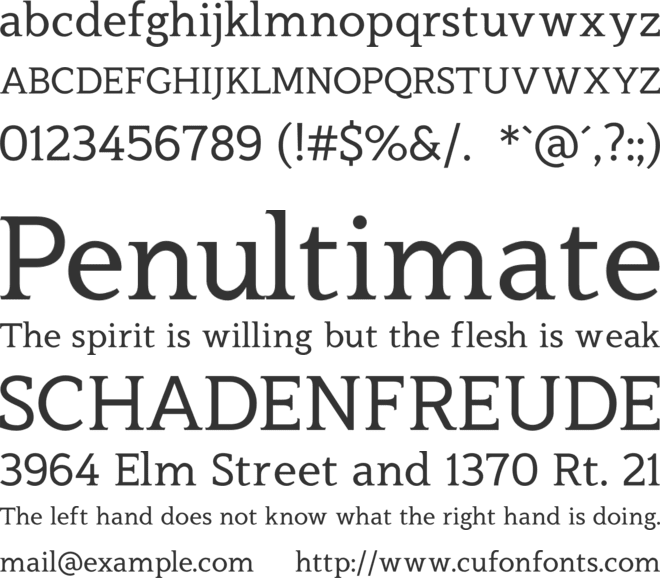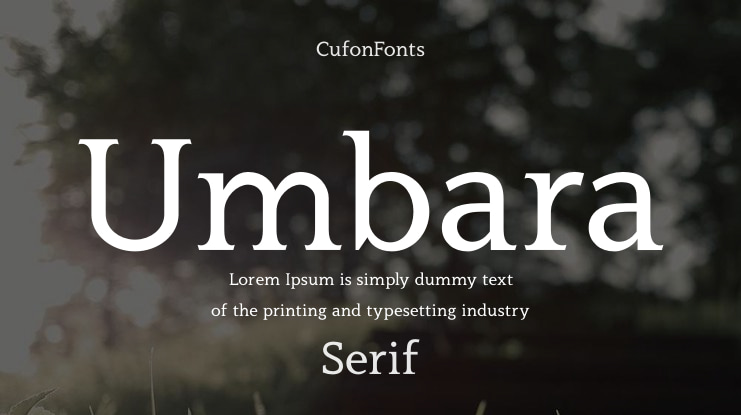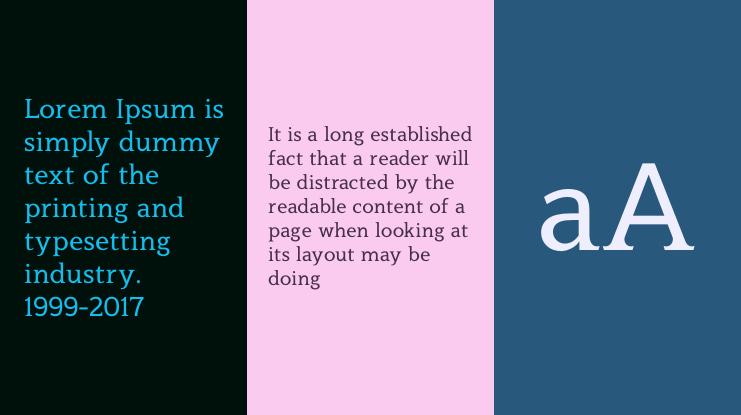
Umbara Font
A fonte Umbará é uma fonte de leitura serifada original, inspirada no antigo bairro Umbará, em Curitiba, Brasil. Foi idealizada por Kawany Novak e desenvolvida pelo estudante universitário Marcus Nakamura, como parte do seu TCC em Design Gráfico na Universidade Tecnológica Federal do Paraná.
A fonte contém mais de 140 glifos no sistema básico de escrita latina, suportando principalmente os idiomas português, inglês e espanhol. Apresenta um conjunto de glifos alternativos para a maioria das letras maiúsculas, conferindo uma personalidade única.
The Umbará Typeface is an original serif reading font, inspired by the old Umbará
neighborhood of Curitiba, Brazil. It was conceptualized by Kawany Novak and designed by college student Marcus Nakamura, as part of his cornerstone project in Graphic Design at the Universidade Tecnológica Federal do Paraná.
The font comprises more than 140 glyphs in the basic latin writing system, mainly
supporting the Portuguese, English and Spanish languages. It features a set of alternative glyphs for the majority of the uppercase letter, granting
a unique personality.